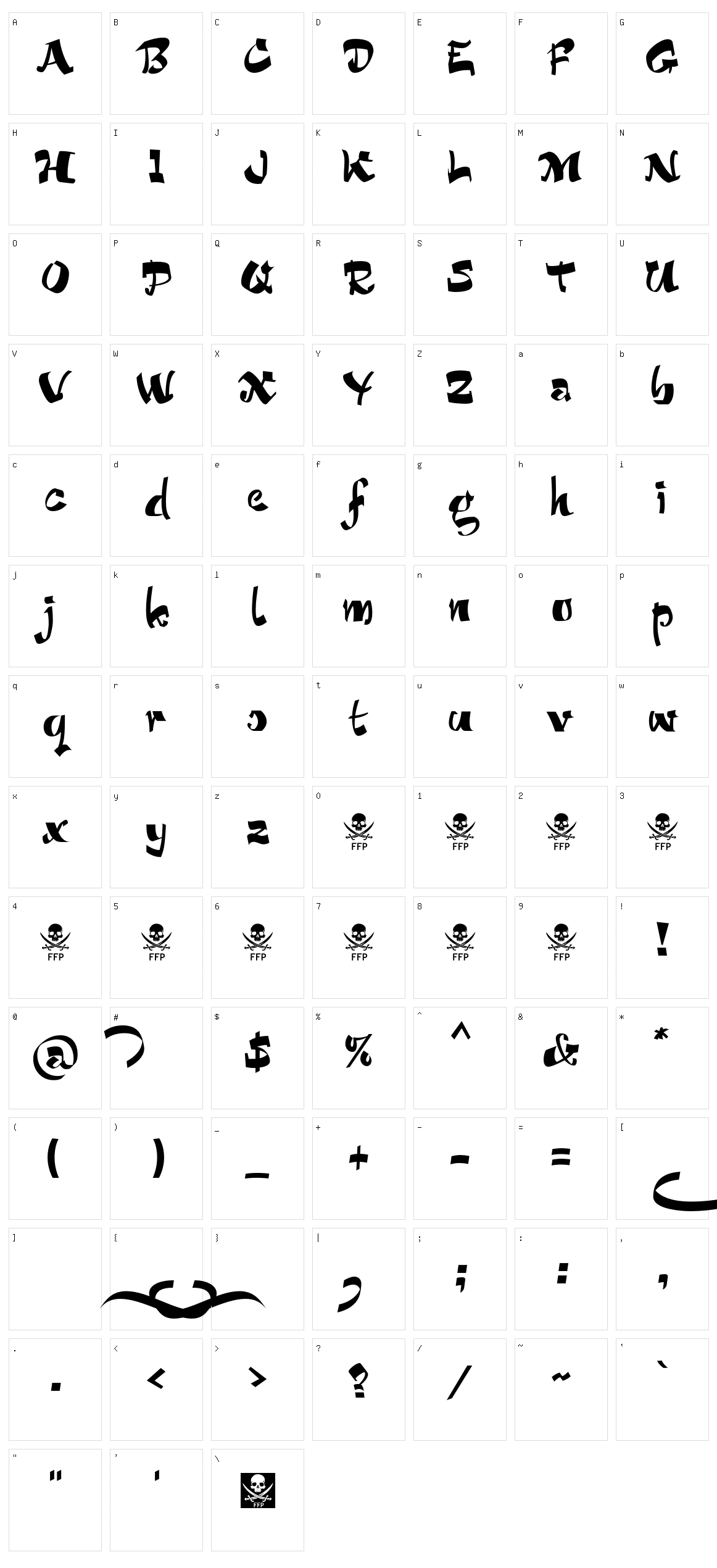
Bucanera dispone de varios adornos dependiendo del contexto y la tecla en que se use:
Tecla: [
1) Voluta inicial larga descendente conectada con la primera letra de una palabra.
2) Usada al final de una palabra con la función Open Type Swashes se consigue un adorno terminal centrado desconectado de las letras.
Tecla: ]
1) Voluta terminal larga descendente conectada con la última letra de una palabra.
2) Usada al principio de una frase con la función Open Type Swashes se consigue un adorno inicial centrado desconectado de las letras.
Tecla: {
1) Voluta inicial media descendente conectada con la primera letra de una palabra.
2) Usada al final de una palabra con la función Open Type Swashes se consigue un adorno terminal centrado desconectado de las letras.
Tecla: }
1) Voluta terminal media conectada con la última letra de una palabra.
2) Usada al principio de una frase con la función Open Type Swashes se consigue un adorno inicial desconectado de la palabra.
Tecla: ¬
1) Adorno terminal medio descendente unido a la última letra de una palabra.
2) Usado al final o principio de palabras con la función Open Type Swashes se consiguen volutas dobles separadas de las letras.
Tecla: |
1) Ornamento terminal corto descendente unido a la última letra de una palabra.
Tecla: #
1) Ornamento terminal corto ascendente unido a la última letra de una palabra.
Buccaneer has several ornaments depending on the context and the key is used:
Key: [
1) Scroll down initial long connected with the first letter of a word.
2) Used at the end of a word and the Open Type 'Swashes' function is achieved, a terminal motif centered off the letters.
Key: ]
1) Scroll down long terminal connected to the last letter of a word.
2) Used at the beginning of a sentence and the Open Type 'Swashes' function is achieved, an initial motif centered off the letters.
Tecla: {
1) Voluta inicial media descendente conectada con la primera letra de una palabra.
2) Usada al final de una palabra con la función Open Type Swashes se consigue, un adorno terminal centrado desconectado de las letras.
Key: }
1) Volute mean terminal connected to the last letter of a word.
2) Used to start a sentence with the Open Type 'Swashes' function is achieved, an initial motif disconnected from the word.
Key: ¬
1) Volute down terminal means attached to the last letter of a word.
2) Used at the end or beginning of words with the Open Type Swashes function are achieved double scrolls separate letters.
Key: |
1) Short terminal descending ornament attached to the last letter of a word.
Key: #
1) Short terminal ascending ornament attached to the last letter of a word.